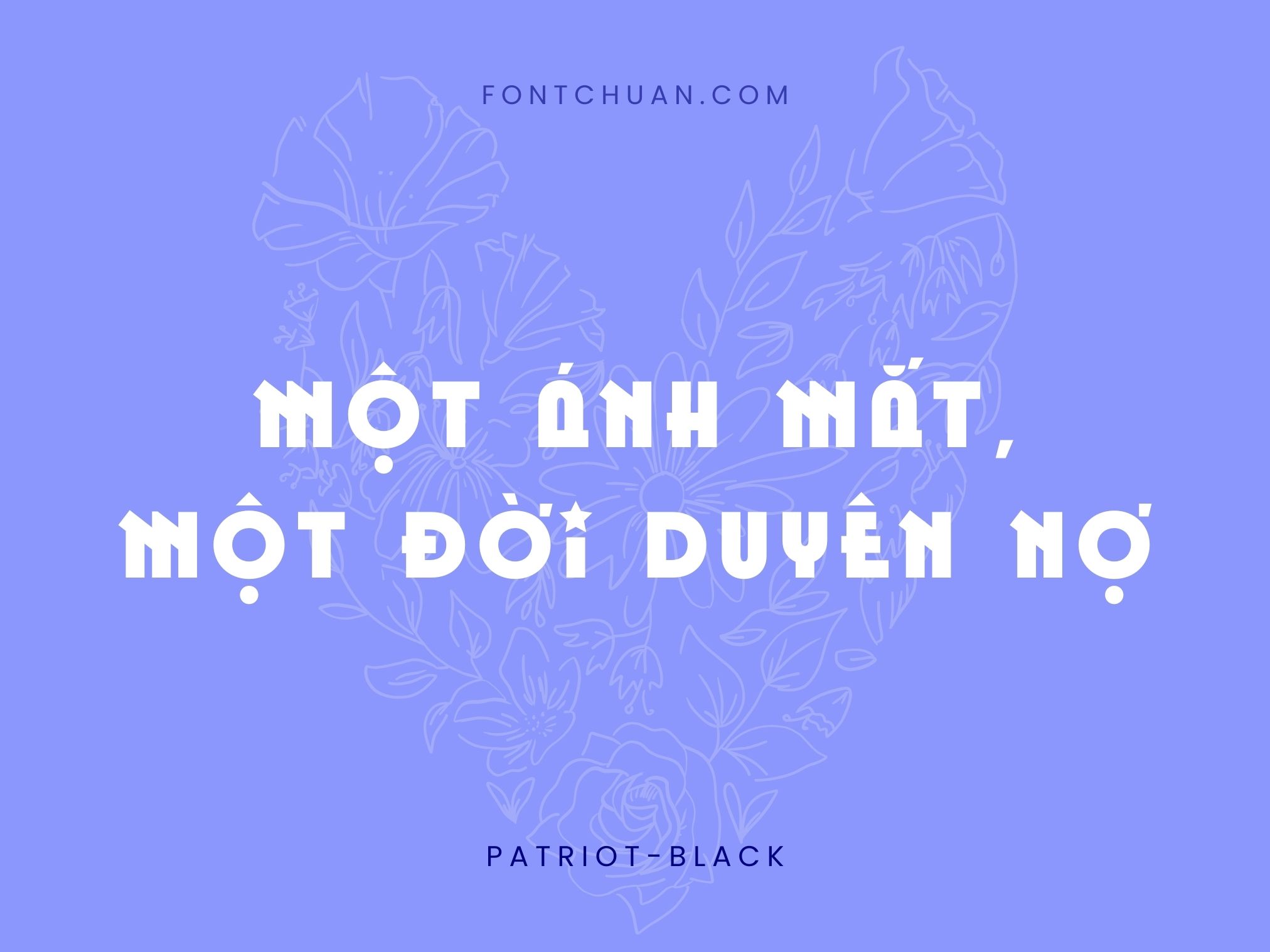
Font Patriot Font Tiếng Việt
Patriot là một font sans-serif hiển thị, được thiết kế bởi Behalf Studio, lấy cảm hứng từ kiểu chữ viết tay trên bìa một cuốn sách nhạc lịch sử được lưu trữ tại Bảo tàng Hồ Chí Minh. Font này thể hiện sự tự tin qua các chữ cái đậm và hữu dụng, với dấu ấn của Art Deco, Bauhaus và Constructivism. Nhờ kiểu dáng mạnh mẽ, sắc nét và dễ nhận diện, Patriot còn được xem là một Font chữ bất động sản lý tưởng, giúp các thiết kế nhận diện thương hiệu, biển quảng cáo hay hồ sơ dự án trong lĩnh vực này trở nên chuyên nghiệp và đẳng cấp hơn. Font hiện có 6 trọng lượng: Light, Regular, Normal, Medium, Bold, UltraBold và Black. Font này hỗ trợ tiếng Việt và nhiều ngôn ngữ khác, được sưu tầm và đăng bởi thành viên của Font Chuẩn.
Font có cấu trúc chữ rõ ràng, các nét chữ đậm và thiết kế độc đáo, tạo nên sự nổi bật và thu hút. Patriot phù hợp cho các thiết kế liên quan đến thương hiệu, tiêu đề, poster và các ấn phẩm truyền thông. Các ngành nghề như quảng cáo, công nghệ, giáo dục và bất động sản có thể tận dụng hiệu quả font này. Ngoài ra, Patriot cũng thích hợp cho các sự kiện như lễ hội, sinh nhật, ngày Nhà giáo, Valentine, và có thể sử dụng như một Font chữ Giáng Sinh để trang trí thiệp, poster hay banner mùa lễ hội, tạo nên không khí ấm áp, vui tươi và rộn ràng cho các sản phẩm thiết kế.